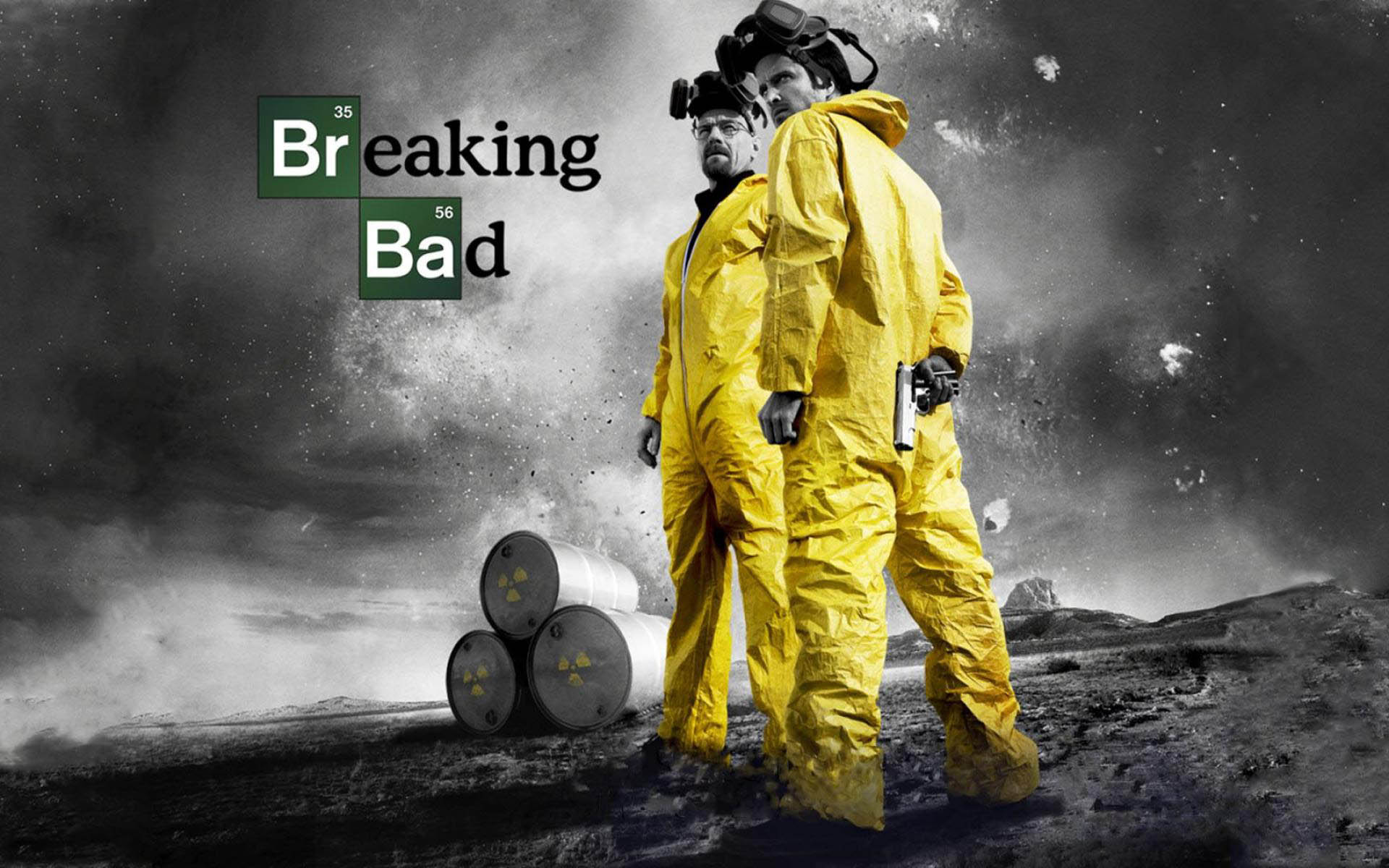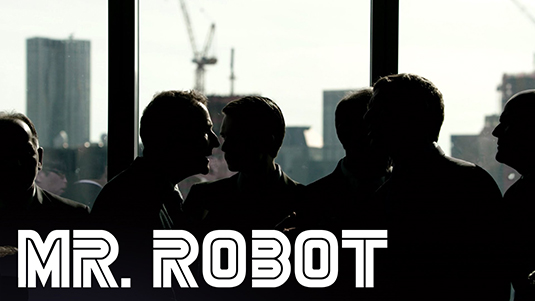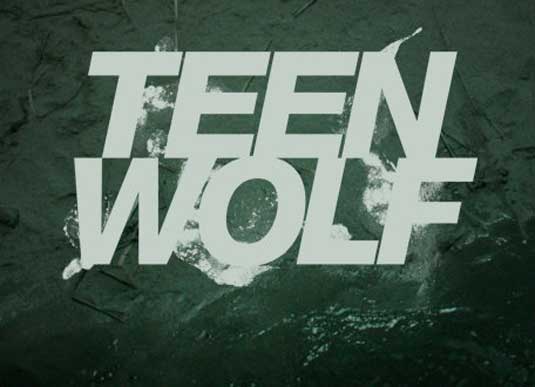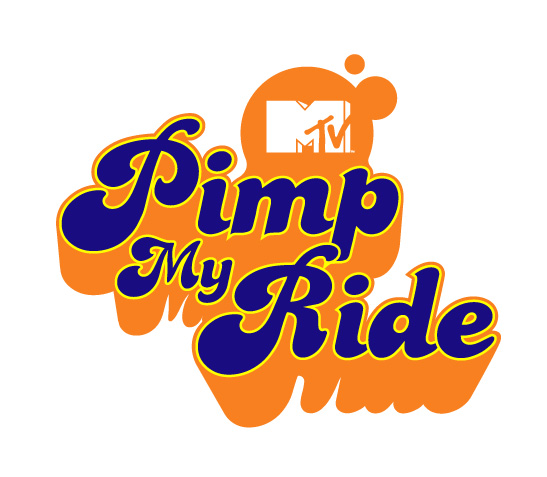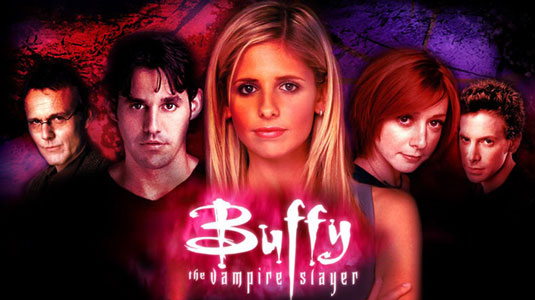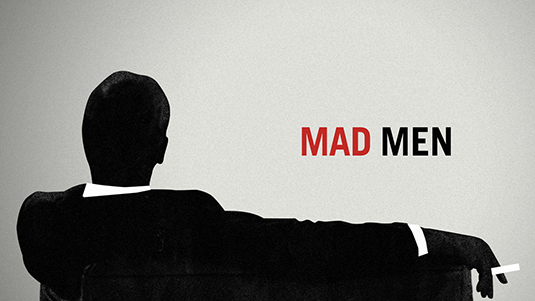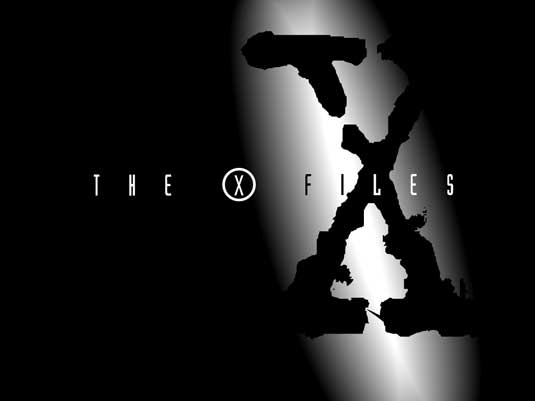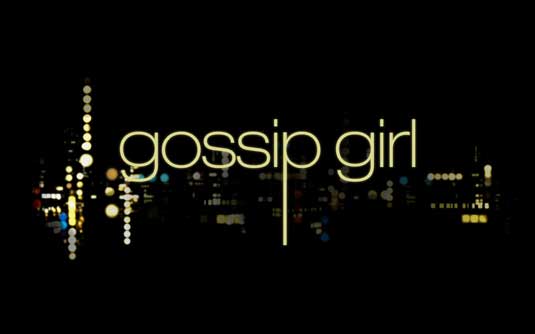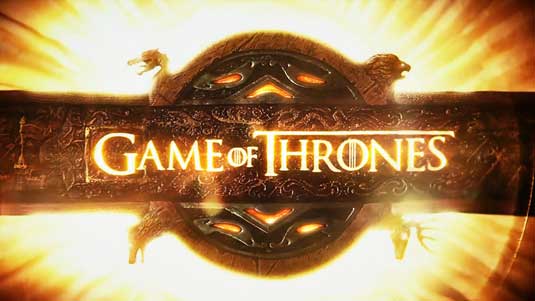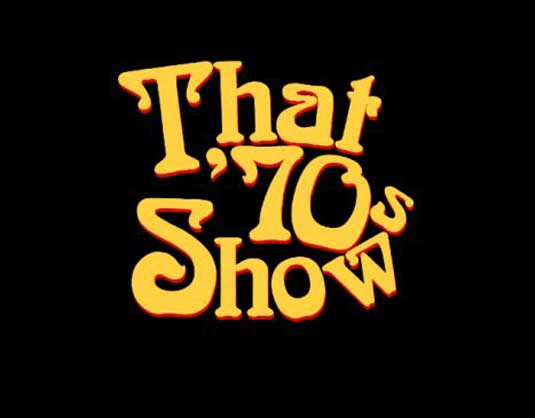
Doce usos geniales de tipografías en diseños de logos televisivos
El buen uso de la tipografía puede hacer que los diseño de logos televisivos sean tan memorables como los personajes e historias.
Cuando nos enamoramos de una serie de TV, por lo general, las cosas pequeñas —el tema, los créditos de apertura, el eslogan— son las que provocan las respuestas emocionales. Y con este enfoque cuidadosamente considerado hacia la tipografía, el diseño de logo puede unirse a este panteón de elementos televisivos icónicos.
En este artículo, Staff Digital ha recopilado diez series de televisión de los 90 y más que realizaron un buen uso de la tipografía y estilo de fuente. Ya sea que estés creando diseños de logos para una una marca de entretenimiento u otra, es seguro que este artículo te inspirará.
1. Mr. Robot
El drama del perturbador hacker de USA Network, Mr. Robot, ha recibido aplausos por ser la serie de televisión que más se ha acercado a comprender el mundo del hackeo. La fuente retro y original Battlestar Galactica escogida para el diseño de logo da un estilo tecno al programa y, al mismo tiempo, añade una vibra tipo cómic.
2. Mad Men
Producido por Imaginary Forces como parte de una secuencia de apertura que debe mucho a Saul Bass por no ser totalmente retro, el diseño de logo de Mad Men representa de manera hermosa y efectiva la dualidad del tema de las series de culto.
3. The X Files
La serie de investigación de extraterrestres The X Files ( o los Expedientes Secretos X, como la conocemos en Latinomérica) no solo revolucionó la ciencia ficción televisiva en los noventa, sino que también mostró un buen manejo de la tipografía. No había necesidad de fotografía y ilustraciones para vender la serie: este buen uso de una tipografía gastada todo lo que se necesitada para transmitir una sensación turbulenta y misteriosa.
4. Gossip Girl
Basada en la fuente Helvetica LT, el diseño de logo de Gossip Girl es tan clásico y sofisticado como los personajes de la serie juvenil. La extensión de la “p” muestra cómo solo necesitas uno o dos sutiles cambios para realizar un transformación de una fuente sencilla a un diseño de logo identificable.
5. Game of Thrones
Para realzar el elemento de fantasía, el diseño de logo de este exitosa serie de HBO añade, astutamente, tres líneas celtas en las O. La presentación de las letras con fuego que brilla a través del meta te deja sin duda acerca del tipo de serie que es.
6. Breaking Bad
Si aún no has visto Breaking Bad, ¿dónde has estado? La intoxicante serie sigue a un tipo que prepara metanfetamina de cristal, y el diseño de logo toma el tema de química y lo usa. El logo usa la fuente Helvetica Bold para la “Br” y la “B” jugando con tabla periódica de elementos y Cooper Mt BT para las demás letras.
7. Friends
La comedia acerca de seis neoyorquinos tiene un diseño de logo que es tan familiar como el elenco. El tratamiento de la fuente puede parecer un poco desactualizada ahora, pero, sin duda, resume el espíritu de los 90 y es, bueno, amigable.
8. That ’70s show
Aquí hay otro tratamiento tipográfico que resume una era sin necesidad de imágenes. Pero que no te tomen el pelo: la fuente no es de los 70. Es Arnold Böcklin, probablemente la mejor fuente Art Nouveau, diseñada en 1904 por Otto Weisert.
9. Californication
Esta serie “dramática” acerca de un novelista perturbado trata de romper los límites. Su diseño del logo garabateado, basado en una fuente personalizada, tiene un efecto curvo que es bastante llamativo y, ciertamente, atractivo.
10. Teen Wolf
La reciente serie televisiva de la clásica película del hombre lobo Michael J Fox necesitaba un logotipo que luzca moderno para diferenciarlo de la serie de los 80 que tenía un poco de comedia, y este tratamiento tipográfico bien marcado y sencillo hace el trabajo a la perfección. El humo alrededor de las letras, que son Helvetica Black Oblique, añade un toque interesante y contemporáneo a la diseño.
11. Pimp my Ride
Tipografía de moda de los 70, con colores estridentes. El diseño de logo para esta serie de MTV acerca de carros personalizados crea una inmediata sensación interesante que es perfecta para Pimp My Ride.
12. Buffy the Vampire Slayer
Júntense, niños, y les contaremos un secreto. En los 90 —antes de ByzAantium, Twilight y Tru-Blood— estaba la mejor y original serie de vampiros adolescentes, Buffy the Vampire Slayer. Su diseño de logo, al igual que su personaje principal, tenía algo extremadamente bello en él: la “f” central que se asemeja a una daga en medio del diseño. Clásico.